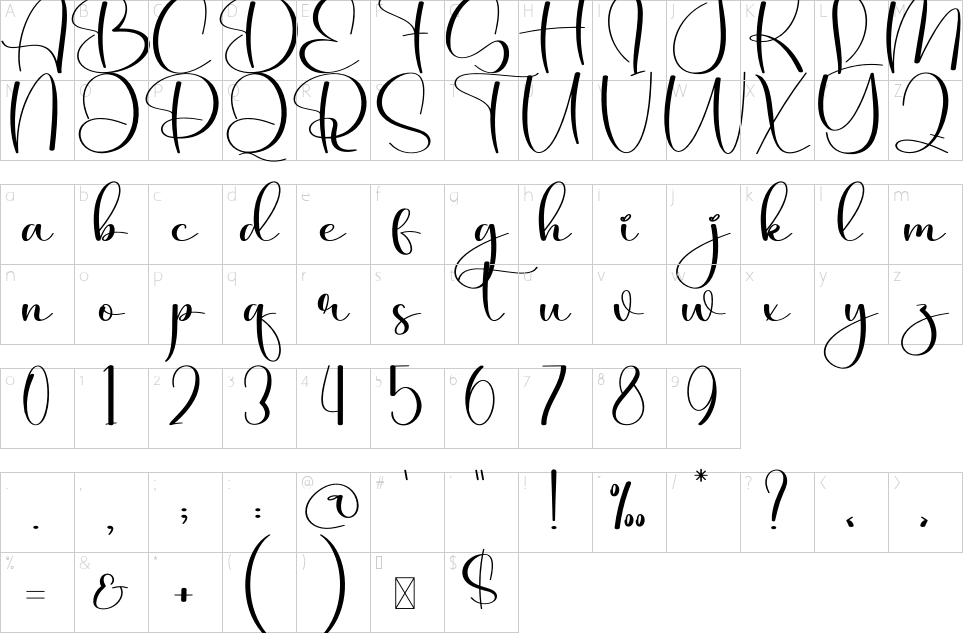
Descubra a beleza natural e moderna da fonte Greating, uma opção gratuita para designers e criativos. Especialmente projetada pela designer anônima do ScratchOne, essa fonte vem inspirar e enriquecer seus projetos de design, seja ele digital ou impresso. Greating oferece uma variedade de estilos elegantes que podem ser usados em qualquer tipo de layout visual, desde materiais gráficos até artes digitais. Se você está procurando por um recurso fonte de graça que não comprometa a qualidade do seu trabalho, Greating é perfeito para essas necessidades. Esta fonte foi especialmente projetada para atender a uma ampla gama de aplicativos: desde o design gráfico e editoriais até os arquivos de texto padrão. Com 364 downloads ao longo dos anos, essa fonte prova sua eficiência e qualidade entre designers e criativos. Com Greating, você pode adicionar um toque único a seus projetos sem pagar nada – uma opção imbatível para quem busca recursos gráficos de alta qualidade.